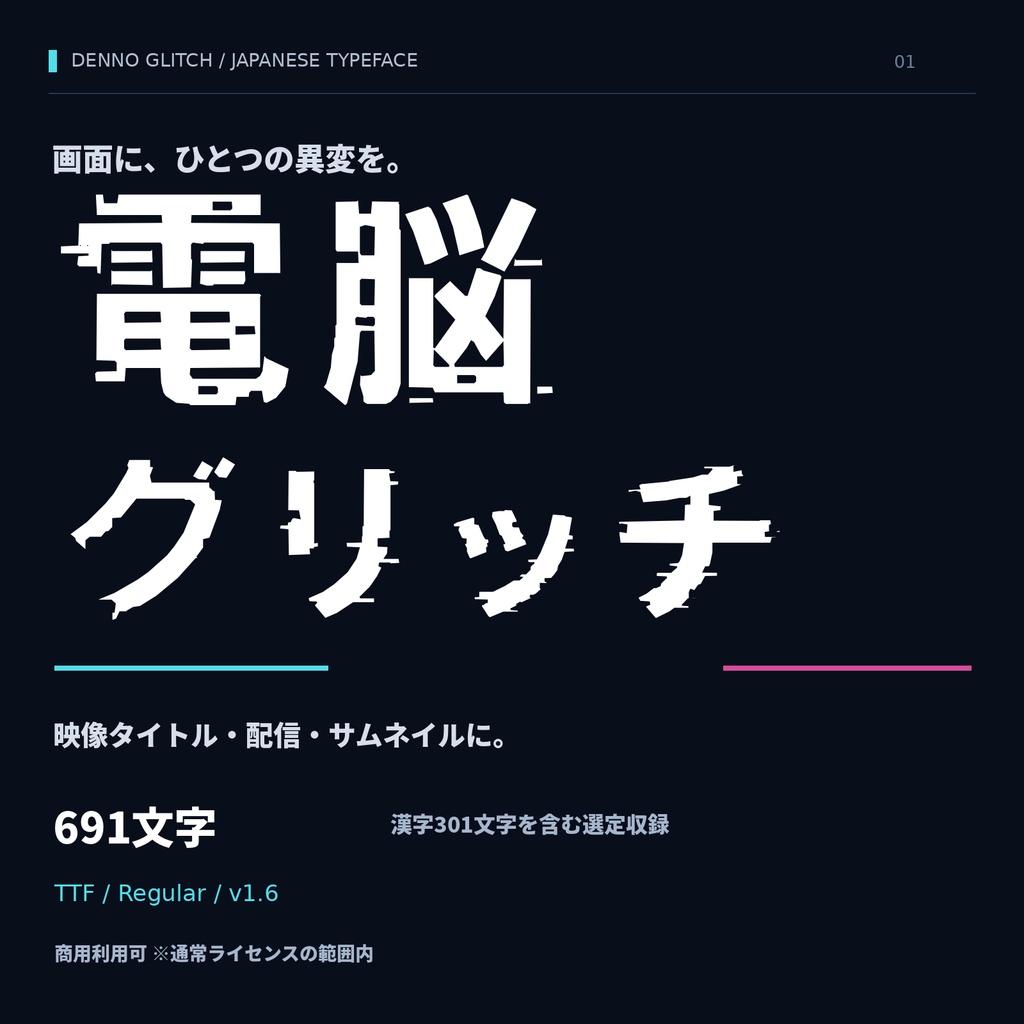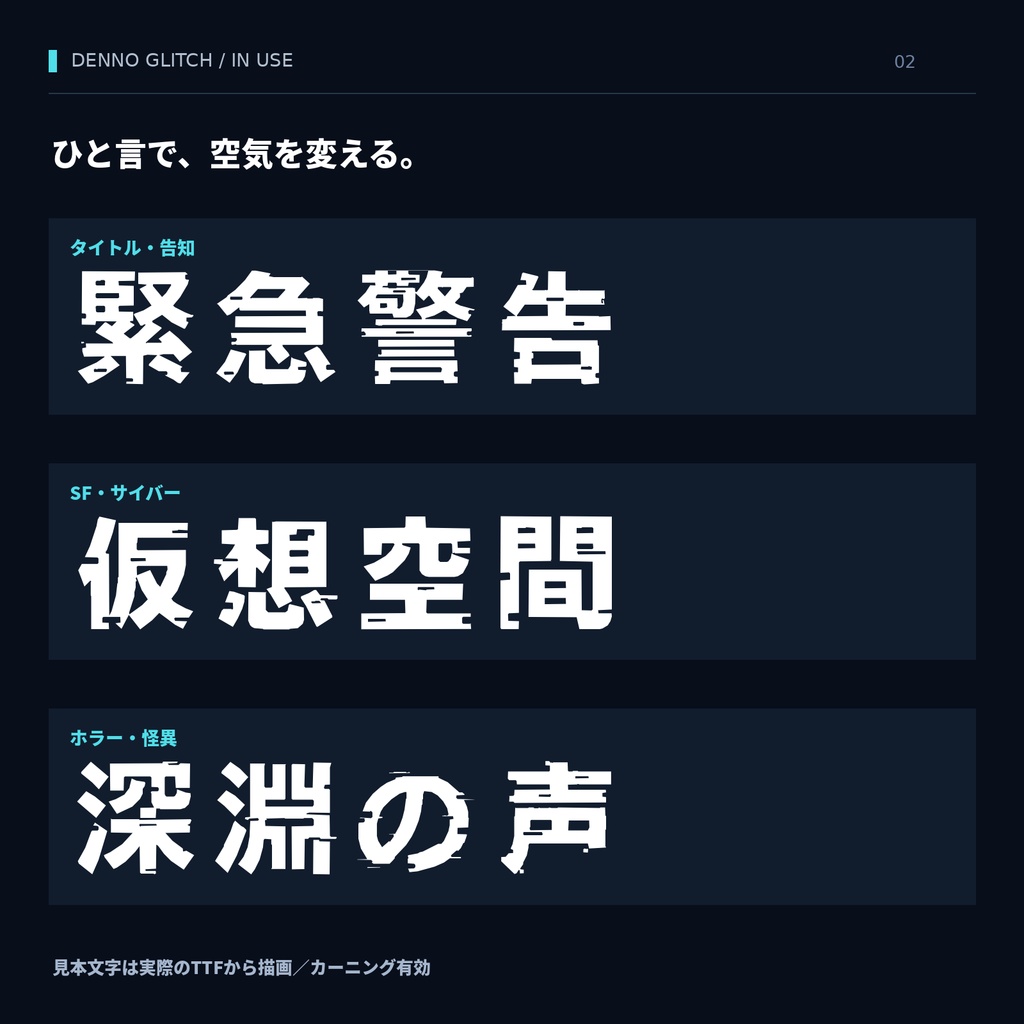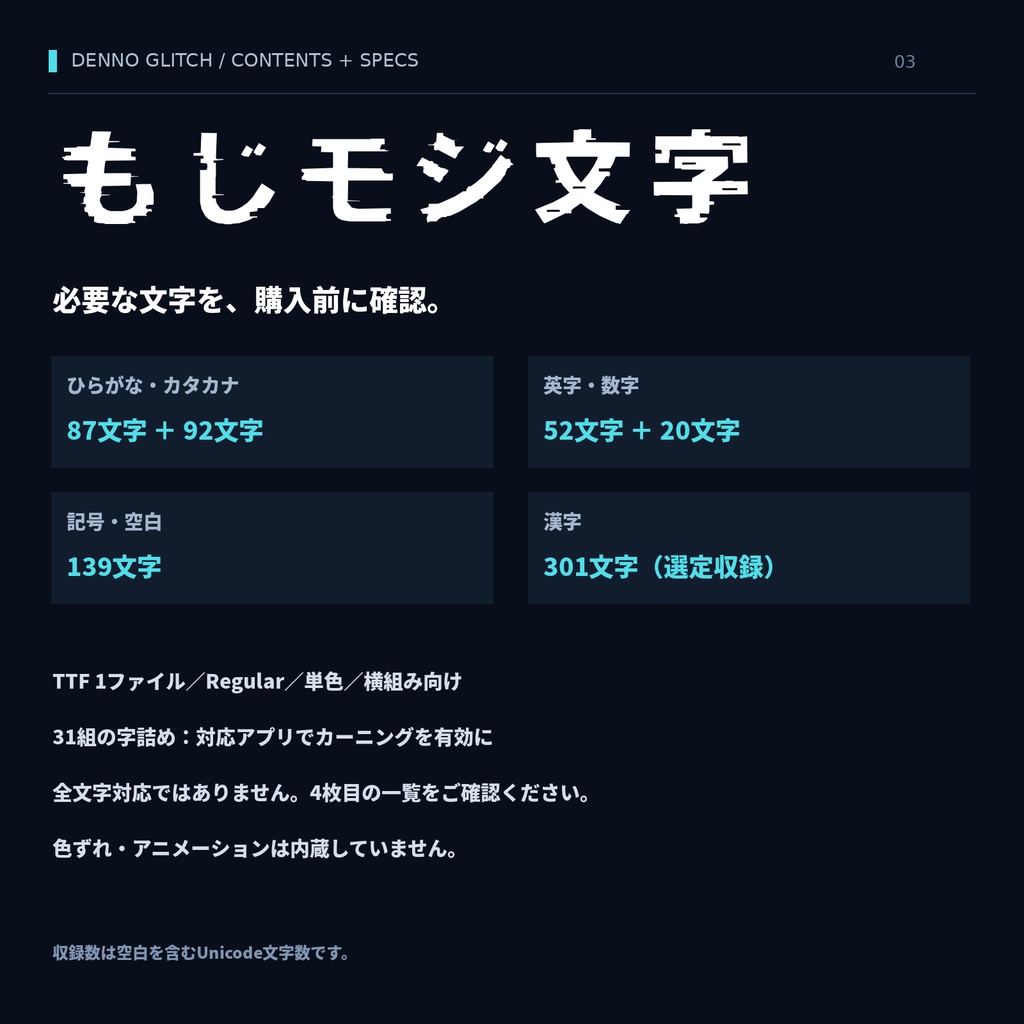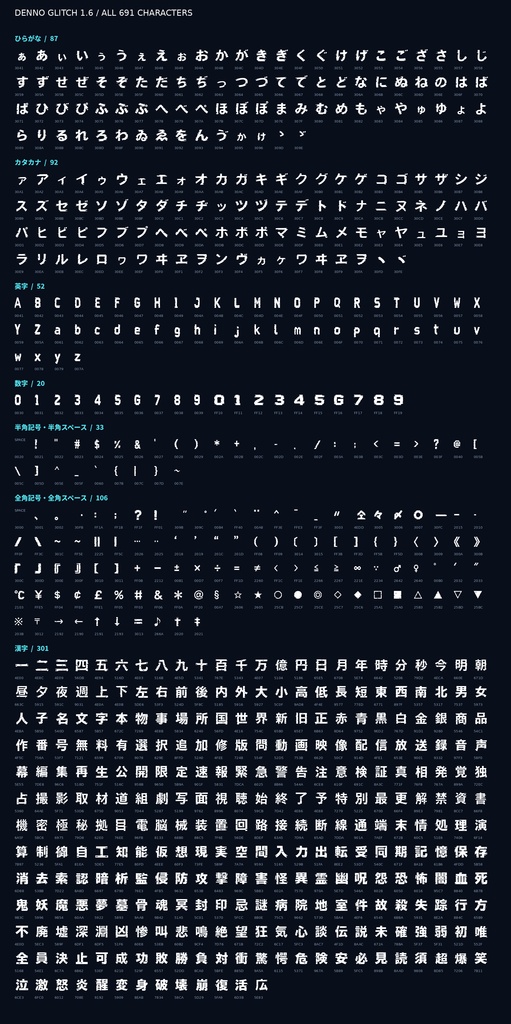
【商用利用可】電脳グリッチ|日本語グリッチフォント・691文字収録【TTF】 画面に、ひとつの異変を。 「電脳グリッチ」は、不規則な横ズレと欠けを字形に組み込んだ日本語フォントです。 太い文字の存在感と、信号が乱れたような表情を、映像タイトルや配信画面、 サムネイル、告知画像に。SF・サイバー・ホラーの見出しにも使えます。
■ 特徴
・文字そのものに横ズレや欠けを持つグリッチデザイン ・ひらがな、カタカナ、英字、数字、記号、選定漢字301文字を収録 ・小書きかなの位置と、濁点付き文字の本体サイズを調整 ・「グリッチ」「コンピュータ」「チェック」など、31組のペア字詰めを搭載 ・通常ライセンスの範囲内で個人・商用利用が可能
■ 収録文字
合計691文字(空白を含む) ひらがな87文字/カタカナ92文字/英字52文字/数字20文字 半角記号・半角スペース33文字/全角記号・全角スペース106文字/漢字301文字 漢字は選定収録です。一般的な日本語の全文字には対応していません。 購入前に全文字表で、使用したい文字が含まれるかご確認ください。 収録外の文字は、使用アプリにより別フォントや未収録記号で表示されます。
■ 表示・字詰めについて
フォント本体は単色です。文字色は使用アプリで変更できます。 シアン/マゼンタの色ずれやアニメーションは内蔵されていません。 見本の装飾線や背景はフォントに含まれません。 ペア字詰めは、対応アプリでカーニングが有効な場合に適用されます。 すべてのカタカナの組み合わせを自動調整する機能ではありません。 アプリ独自の自動字詰めとの併用時は、表示をご確認ください。 横組み向けです。縦組み専用の調整は行っていません。 長音符「ー」は全角で、半角長音符「ー」は未収録です。 一部の旧仮名コードは清音と同じ字形です(ヷ→ワ、ヸ→ヰ、ヹ→ヱ、ヺ→ヲ)。